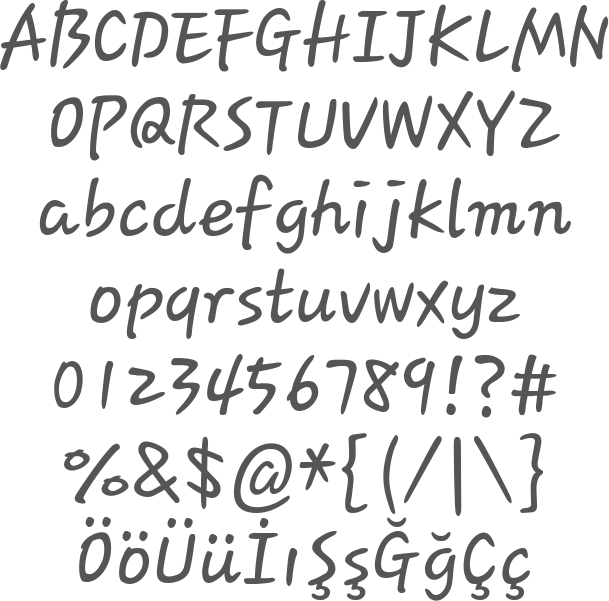
Eventuell aus Android Smartphone? Ähnlich YD Summer Bold
Habe leider nur dieses Bild als Beispiel. Es könnte aus einer Notiz-App stammen, die man auf eine Systemschriftart umstellen kann, bspw. auf einem Android Smartphone. Ist aber nur eine wilde Spekulation.
Mit den verschiedenen Font Identifier Websites kam wenig Brauchbares heraus, die beste Näherung war "YD Summer Bold". Die hat jedoch bspw. nicht das sehr markante kleine "m" aus meiner Grafik.
Create the Face of Galaxy Devices: Font Designer JiEun Kim
Das sind also Systemschriften für Android von Samsung, gestaltet von JiEun Kim. Da werden folgende Schriften genannt:
•  Choco Cooky
•  Cool Jazz
•  Gothic Bold
•  Rosemary
•  Samsung Sans
Das hilft zwar nicht so sehr für die Suche bei bereits bekanntem Namen, aber sehr für das Verständnis. So einen richtig offiziellen Download habe ich bis jetzt auch nicht gefunden.